Une écriture cursive
La typographie arabe est avant tout un système d’écriture cursif, un tracé vivant où les lettres se relient pour former un mot. Contrairement aux alphabets latins, où chaque caractère s’aligne indépendamment, les polices arabes se déploient dans un mouvement continu, suivant le rythme de la phrase.
Chaque lettre change de forme selon sa position — initiale, médiane, finale ou isolée — donnant à la typographie arabe un sens unique du flux, de la cohérence et du mouvement.
Cette fluidité fait de l’arabe non pas seulement un alphabet, mais une chorégraphie de formes où le geste et le sens se confondent.
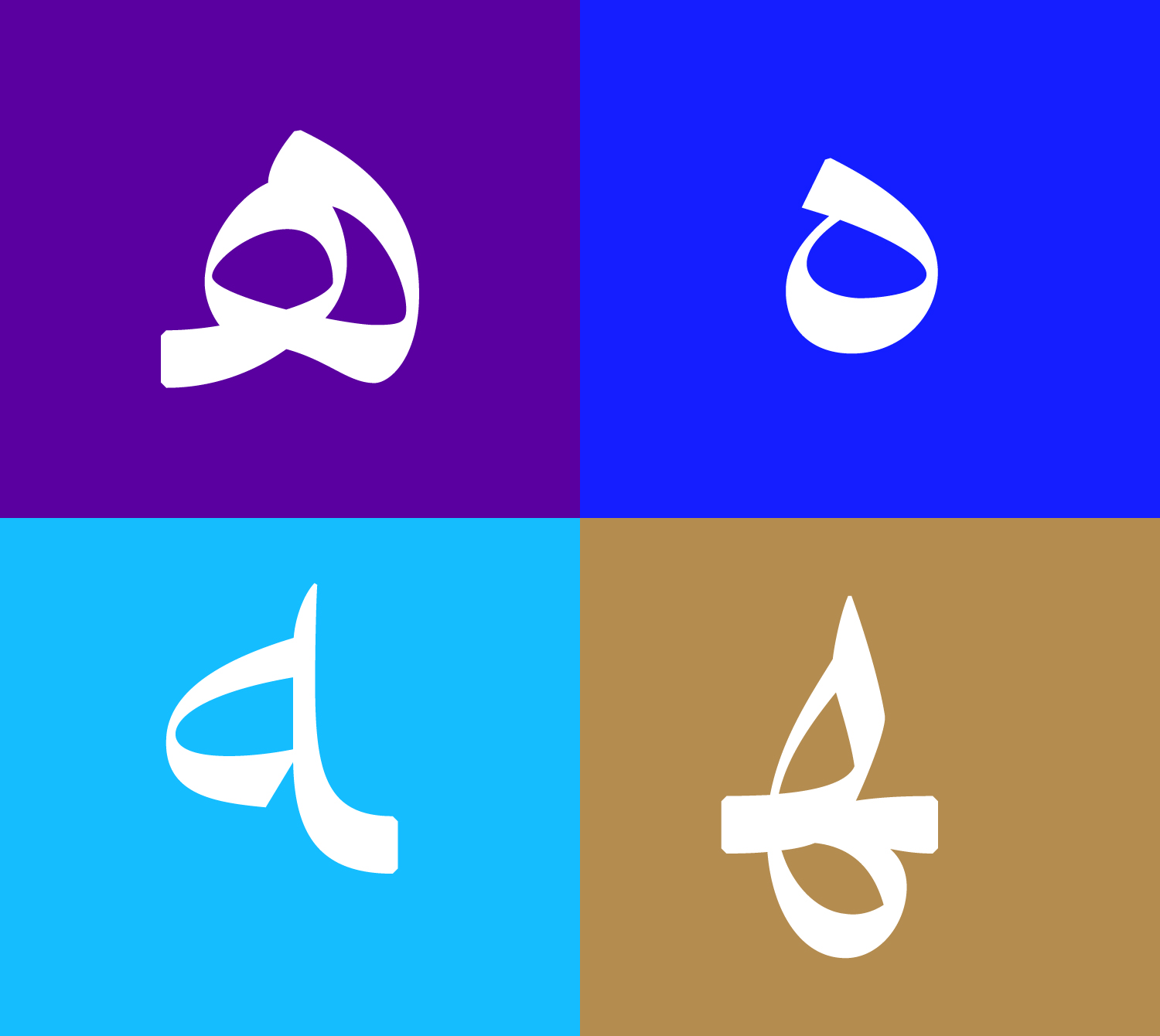
En raison de cette structure connectée, les polices de caractères arabes reposent sur des formes contextuelles : chaque lettre s’adapte à ses voisines pour préserver l’équilibre visuel et la lisibilité du mot.
Pour le designer contemporain, le défi consiste à conserver l’expressivité calligraphique de l’arabe tout en la traduisant dans la précision d’un dessin typographique numérique.
Chez Babelfont, nous voyons cette démarche comme un dialogue entre expressivité et rigueur, où la calligraphie devient une architecture graphique.
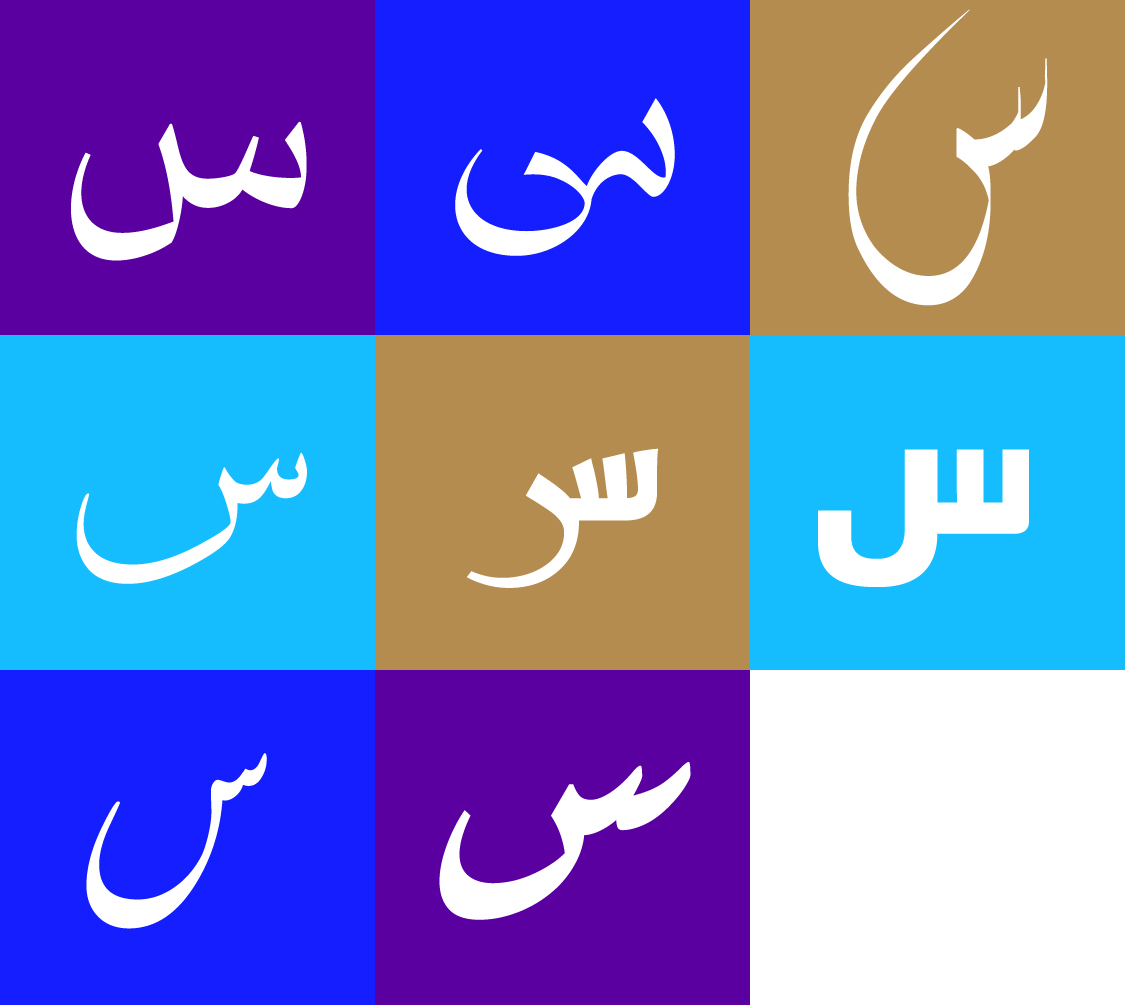
Deux grandes familles qui inspirent la typographie arabe moderne
L’histoire de la calligraphie arabe a produit une dizaine de styles majeurs : Naskh, Thuluth, Diwani, Ruqʿa, Maghribi, Riqaʿ, Taʿliq, Nastaliq, et Kufi, chacun porteur de son rythme, de ses proportions et de son univers visuel.
Ces traditions peuvent toutefois se regrouper en deux grandes familles qui définissent l’essence de la typographie arabe moderne :
• un style fluide et humaniste, issu du Naskh, du Diwani ou du Thuluth, où la ligne s’exprime avec souplesse et mouvement ;
• un style géométrique et structuré, hérité du Kufi, reconnaissable à ses lignes franches, ses angles nets et sa construction architecturée.
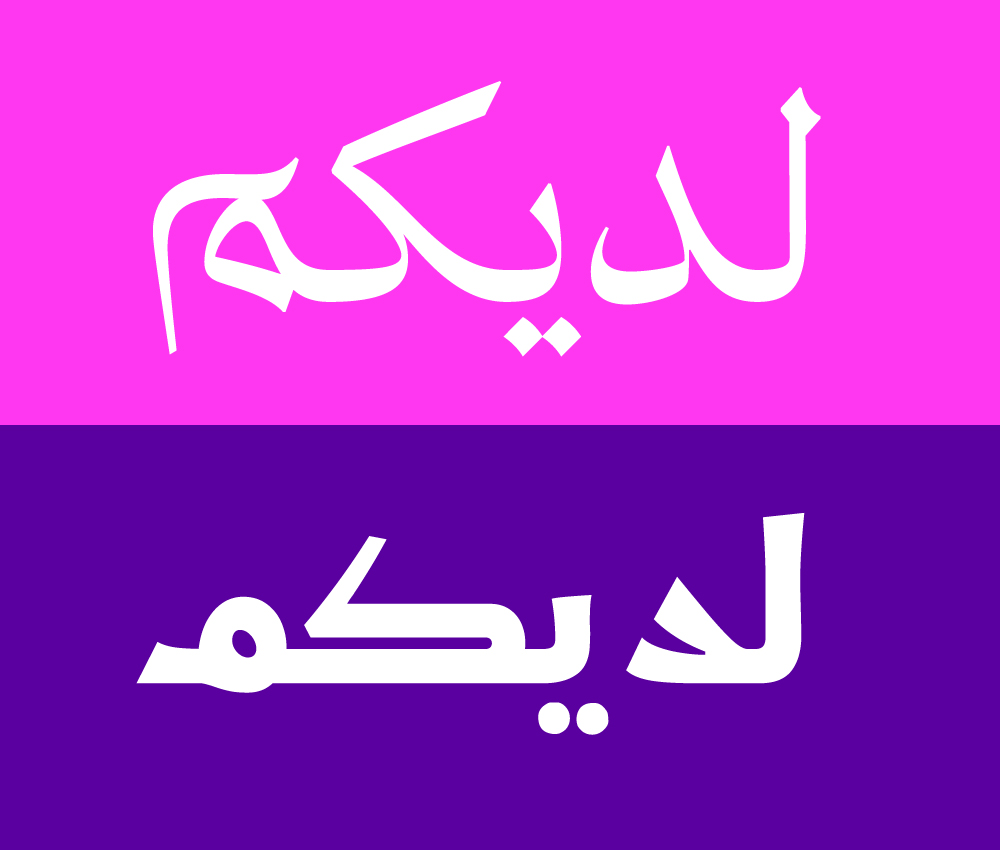
C’est entre ces deux mondes — le geste calligraphique et la forme construite — que se situe le travail de Babelfont.
Notre ambition : trouver l’équilibre entre la sensualité du tracé et la rigueur du système typographique, entre la tradition et la modernité.
Le véritable défi de la création typographique arabe (Arabic font design) est de maintenir cet équilibre — celui d’une écriture à la fois fluide et structurée, héritée du passé mais tournée vers l’avenir.